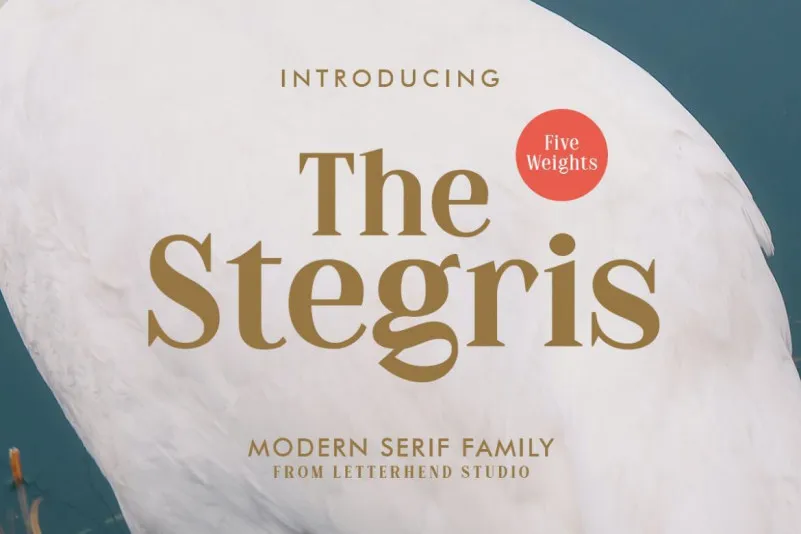
The Stegris Font Family – Download Grátis
Introduzimos The Stegris Font Family, uma família serifada condensada que carrega consigo pequenas irregularidades de design e encontra uma gama única de ligaturas estilizadas, criando um tom distintivo para seus projetos. Este tipo de fonte tem características especiais em sua ligação que a tornam ainda mais singular e capaz de destacar suas criações. The Stegris é perfeito para quem busca destaque na comunicação visual, permitindo uma personalização adequada às necessidades específicas do seu design. Seja você um designer gráfico ou digital, o uso da Stegris pode ajudar a tornar sua identidade visual mais atraente e inovadora.